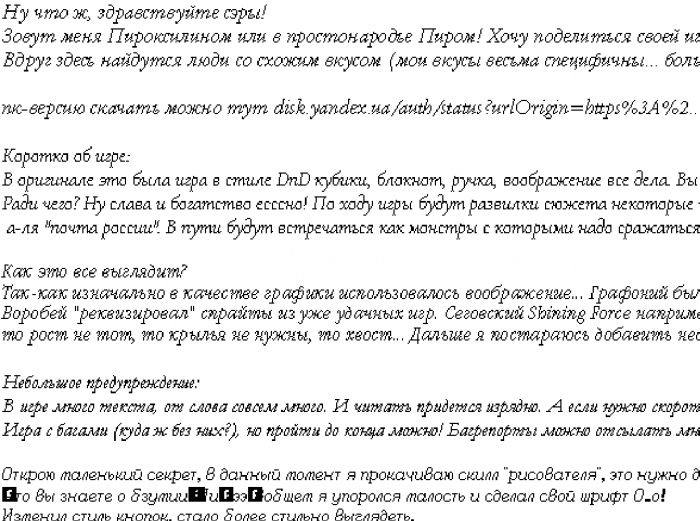
Oh no! A good pixel font with a bad сyrillic, what a pity! I could have fixed it if you had made it open to cloning.
An attractive pixel font in a smaller grid and well italicised. The classic 'Times' look would have been perfect in the present serifcomp.
Reather 'Garamond' look, Aeolien)
Привет, Пироксилин. Если бы не шрифт, так и жил бы, не зная о твоём творчестве. Удачи в твоих начинаниях и продолжаниях)
Я бы мог, конечно, сделать кириллицу лучше, но не буду) Нужна же востребованность какая-нибудь, чтобы это было полезно и использовалолсь, тем более можно растрировать уже существующие хорошие шрифты. На картинке это всё Гарамонд от разных дизайнеров. Второй сверху, Cormorant, как мне кажется, больше всего подходит под твой стиль и бесплатен.
Роль шрифта может показаться не такой большой в восприятии, учитывая, что ему тоже надо учиться, как и рисаванию. В рисовании шрифта же много ньюансов, его "нельзя просто так взять и сделать", но если что — можешь обращаться ко мне. Давно хочу сделать что-нибудь такое, типа почерка Bastard, но вот моей ленивой жопе не хватает мативации.
oof, reminds me of Shining Forces font…